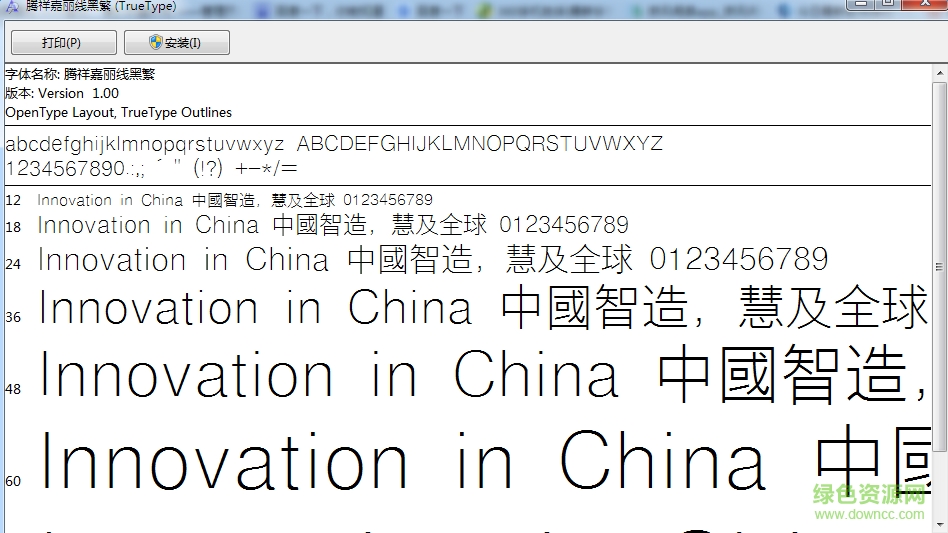
騰祥嘉麗線黑繁字體是一款非常有風格的電腦字體,有些字體只有一般字體的一般高,排版下來就會形成非常具有特色的一個版面,適用于標題及正文排版,可應用于出版印刷、廣告設計、網(wǎng)頁設計、包裝設計、屏幕顯示。喜歡可以來綠色資源網(wǎng)下載!
騰祥嘉麗線黑簡字體風格采用橫豎筆畫無裝飾襯線的設計,以黑體為契機,并選擇部分字形設計成半高尺寸,字形結(jié)構合理、筆畫粗細協(xié)調(diào),空白均勻,使之排版時形成波 浪起伏的跳躍感,從而使排版達到一種特殊的、不規(guī)則的設計效果。